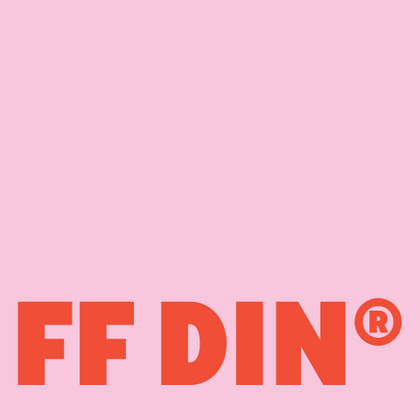
Шрифты похожие на FF DIN®
Шрифт FF DIN® — классический промышленный гротеск, но его техническая эстетика может выглядеть излишне строгой. В TypeType мы разработали современные альтернативы, которые сохраняют рациональность оригинала, но добавляют индивидуальности вашему проекту.
Наши аналоги шрифта FF DIN® особенно хороши для корпоративного брендинга, интерфейсов и цифровых продуктов, навигации и полиграфии.
Если вы устали от «заезженных» шрифтов и ищете гарнитуры, похожие на FF DIN®, ознакомьтесь с нашими лучшими альтернативами FF DIN®. Это шрифты, которые имеют близкие характеристики, но в то же время обладают новыми уникальными особенностями дизайна. Например, относятся к той же категории шрифтов, подходят для тех же целей и имеют похожие черты, но отличаются в деталях или пропорциях.
В TypeType вы найдете передовые шрифты, такие как FF DIN® и даже лучше: вот несколько замечательных и не столь распространенных альтернатив FF DIN®. Используйте этот список высококачественных, выглядящих как FF DIN® шрифтов, на свой вкус. Так вы сможете подобрать еще более для вашего проекта подходящий шрифт, расширив выбор, или освежить свой дизайн. Все шрифты, представленные в этой коллекции, доступны в разных форматах и по доступным ценам, поэтому вы сможете найти тот, который соответствует любым потребностям!
Найдите отличную замену FF DIN® и попытайтесь имитировать похожее настроение, передать нужное вам ощущение, используя его в своих проектах. Каждый шрифт, представленный на этой странице, является двойником шрифта FF DIN®, фактически его полным аналогом.
TT Rounds Neue — мягкий и дружелюбный шрифт, который умеет быть разным. В тонких начертаниях он выглядит минималистично и нейтрально. В жирных же — «надувается» и округляется, приобретая инфантильные черты.
TT Fors — тот самый шрифт «для всего». Это стильный, лаконичный и функциональный геометрический гротеск с выверенными формами. Его можно использовать и в интерфейсах, и для создания акцентов.
TT Ramillas — стильная и современная антиква, которая украсит любой проект. Уникальные декоративные начертания и буквицы с цветочным орнаментом помогут создать неповторимый дизайн. Шрифт уже используется на 3000+ сайтах во всем мире, а также отмечен наградой Modern Cyrillic.
TT Norms Std Condensed является логическим развитием нашего бестселлера TT Norms Pro. Несмотря на то, что шрифт обладает более узкими пропорциями относительно исходной гарнитуры, он унаследовал классические пропорции знаков, внимание к деталям и дотошную проработку каждого знака в шрифте.